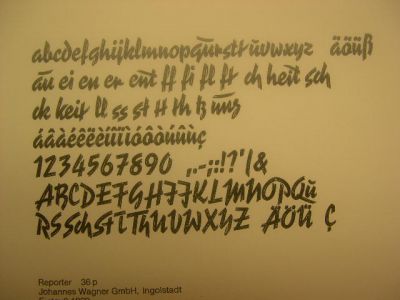
Im gleichen Stil gibt es die Bleisatz-Schrift Reporter - siehe Bild.
Und die wiederum gibt es meines Wissens nach auch als digitalisierte Schrift.
richtig bleisetzer,
es gibt die reporter (1 und 2), aber sie ist es nicht ;)
Ich glaube, das habe ich auch nicht behauptet:
"Im gleichen Stil gibt es die Bleisatz-Schrift Reporter - siehe Bild.
Und die wiederum gibt es meines Wissens nach auch als digitalisierte Schrift."